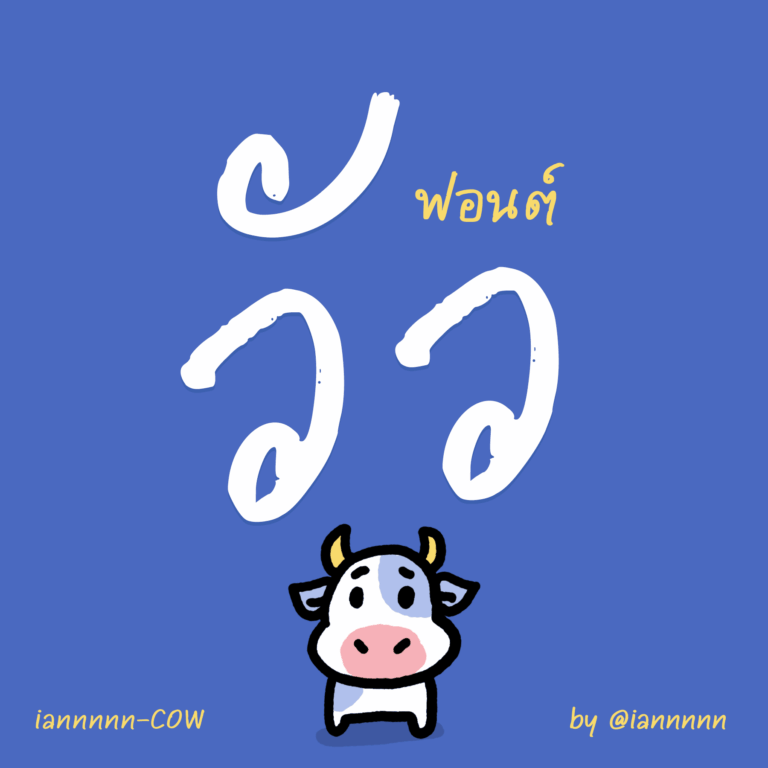
นี่เป็นฟอนต์ตัวที่สามที่ผมหัดทำในโปรแกรม FontCreator เกิดจากความหงุดหงิดเวลาใช้ปากกาลูกลื่นห่วยๆ เขียนกระดาษแล้วดันไม่ยอมติดซะที แม่ง ต้องคอยถูๆ ลากๆ ย้ำๆ จนออกมาเป็นตัวอักษรที่เหมือนขอความช่วยเหลือชาวบ้านอยู่ยังงี้แล.. (จริงๆ แล้วชอบเป็นการส่วนตัว)
iannnnnSOS